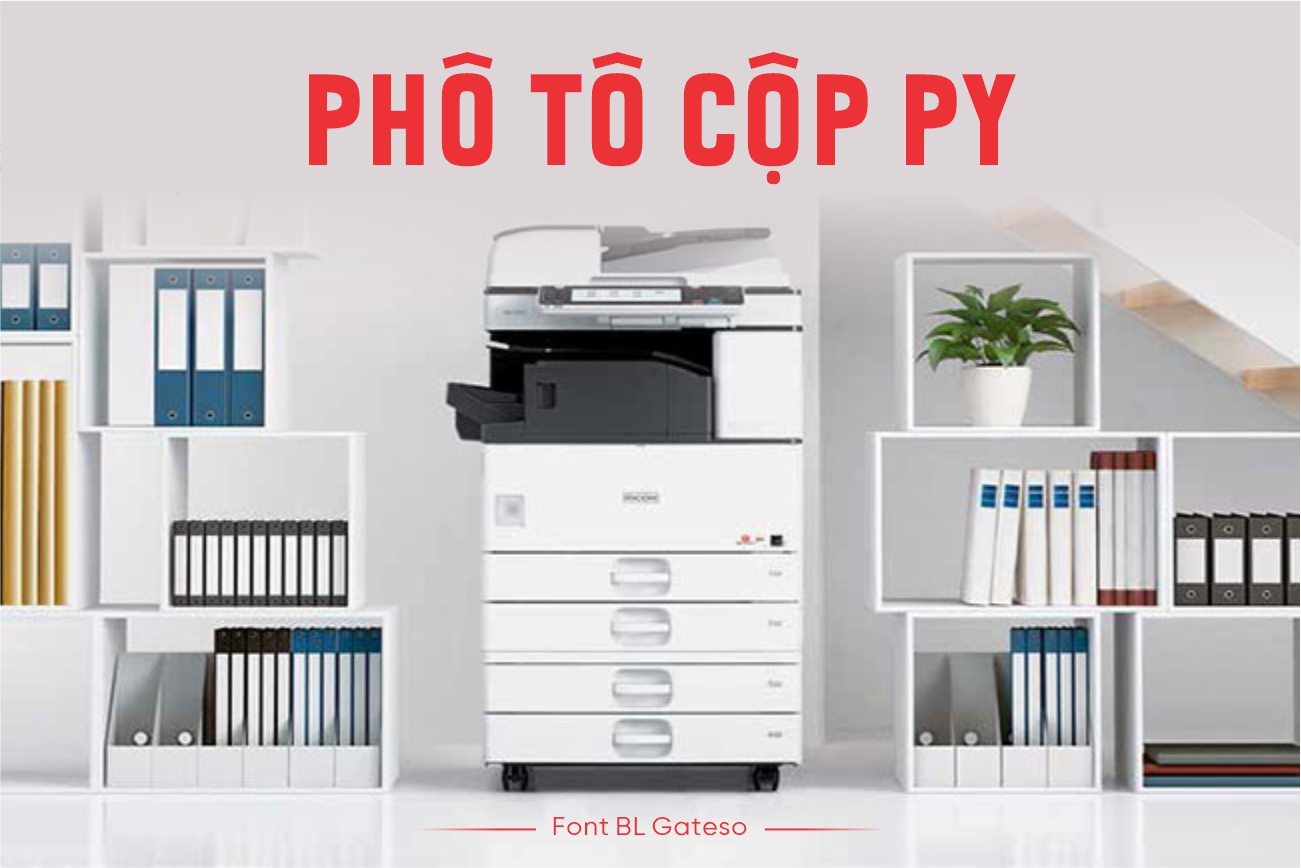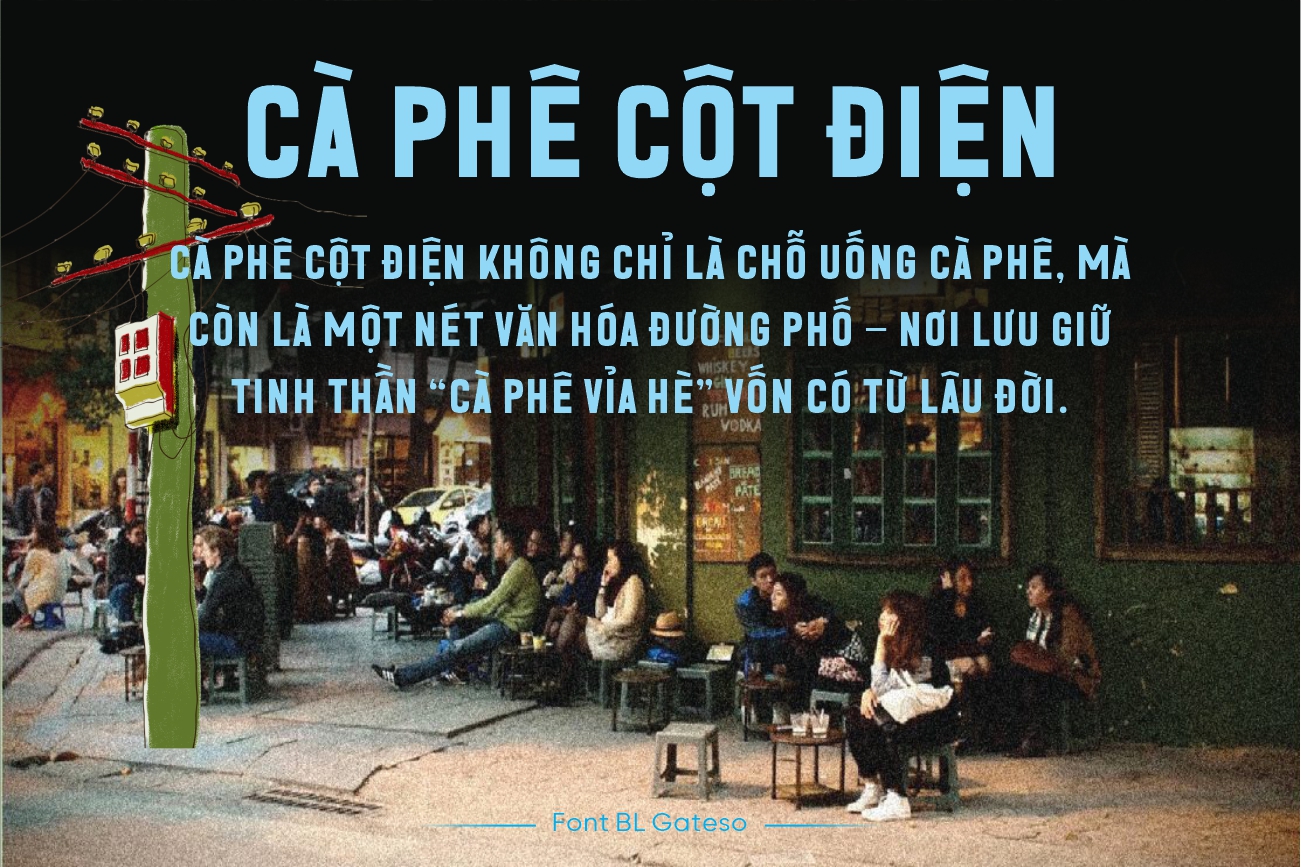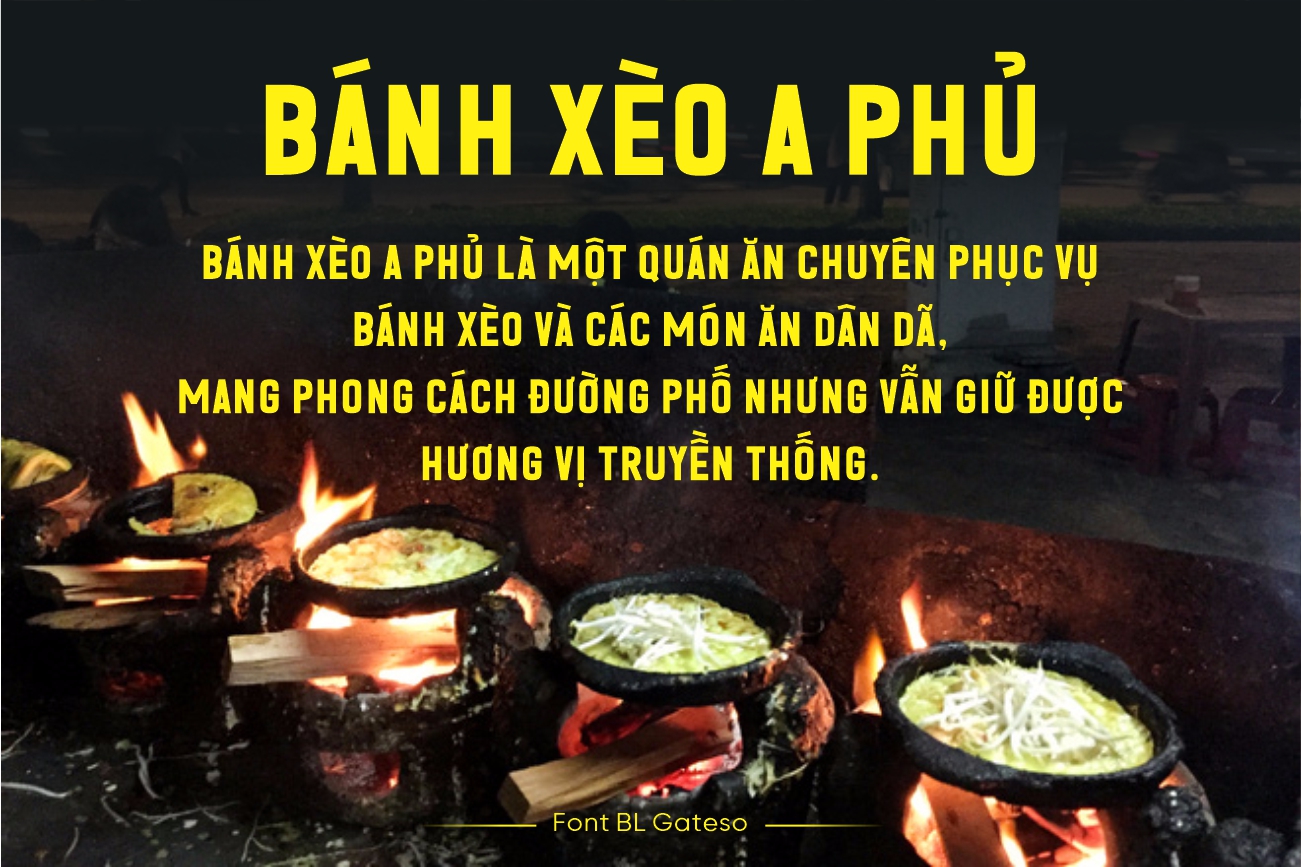
Font hoài cổ, gợi nhớ ký ức bao cấp Việt Nam - BL Gateso Việt hóa
Trong thế giới thiết kế, những kiểu chữ mang hơi hướng xưa cũ luôn có sức hút đặc biệt bởi khả năng gợi nhớ và tái hiện lại bầu không khí của một thời kỳ đã qua. Font BL Gateso chính là một trong những lựa chọn tiêu biểu, được thiết kế gốc bởi Andal (7NTypes) và sau đó được BL Việt hóa hoàn chỉnh để hỗ trợ đầy đủ tiếng Việt.
Với thiết kế mạnh mẽ, dứt khoát, BL Gateso tái hiện gần như nguyên vẹn tinh thần của các font chữ xưa từng xuất hiện trên bảng hiệu “Bách Hóa Tổng Hợp”, “Cà phê Cột Điện” hay “Phô tô cộp py”. Những ký tự in đậm, vuông vức và chắc chắn mang đến cảm giác bền vững, kiên định, phản ánh đúng tinh thần thiết kế trong giai đoạn bao cấp.
Điểm nổi bật của font hoài cổ này chính là sự giản dị nhưng đầy ấn tượng. Không cầu kỳ về chi tiết, BL Gateso lại chinh phục người nhìn bằng sự tối giản, gọn gàng và dễ đọc. Chính sự mộc mạc ấy khiến nó trở thành một trong những font chữ bao cấp được nhiều nhà thiết kế lựa chọn khi muốn tái hiện lại tinh thần retro – vintage trong các ấn phẩm quảng bá, poster, biển hiệu hoặc dự án nghệ thuật.
Ngoài ứng dụng trong thiết kế, BL Gateso còn mang giá trị văn hóa sâu sắc. Mỗi đường nét của font như một “chứng nhân” thị giác, lưu giữ ký ức tập thể về một giai đoạn lịch sử đáng nhớ. Vì vậy, font không chỉ đẹp về mặt thẩm mỹ mà còn giàu cảm xúc, giúp thiết kế của bạn trở nên gần gũi và khác biệt hơn.
Nếu bạn đang tìm kiếm một font hoài cổ, gợi nhớ lại những năm tháng bao cấp, thì BL Gateso chính là lựa chọn lý tưởng. Đây không chỉ là một font chữ xưa đẹp mắt, mà còn là cầu nối tinh thần giữa quá khứ và hiện tại, mang lại sức sống mới cho những thiết kế hiện đại.